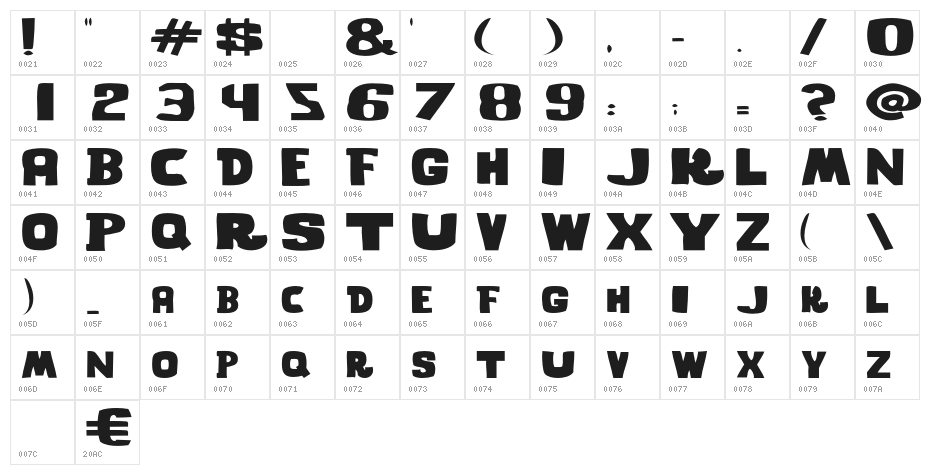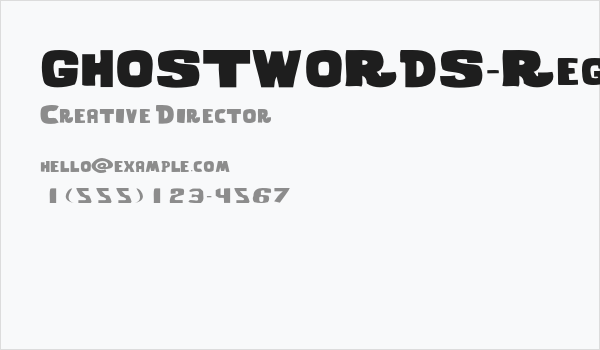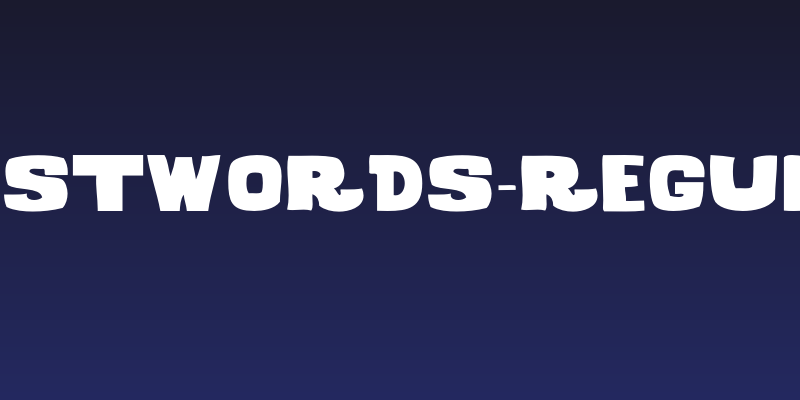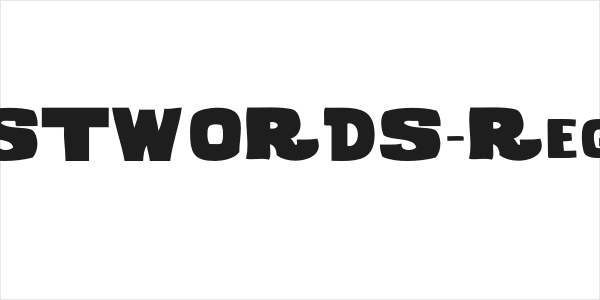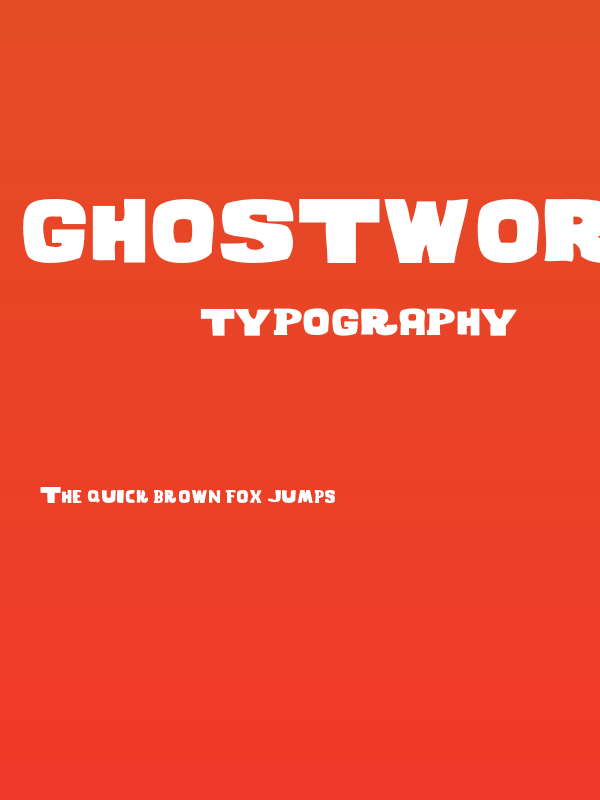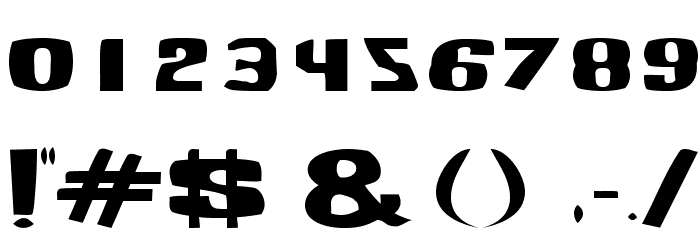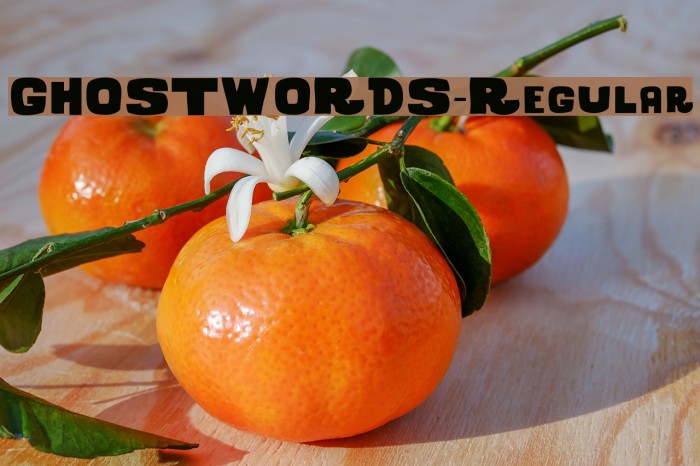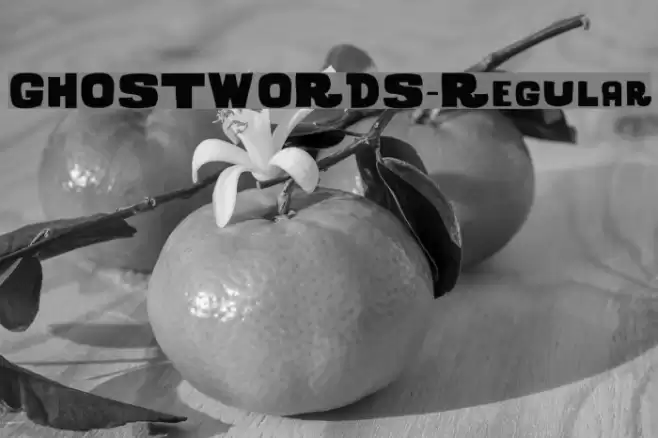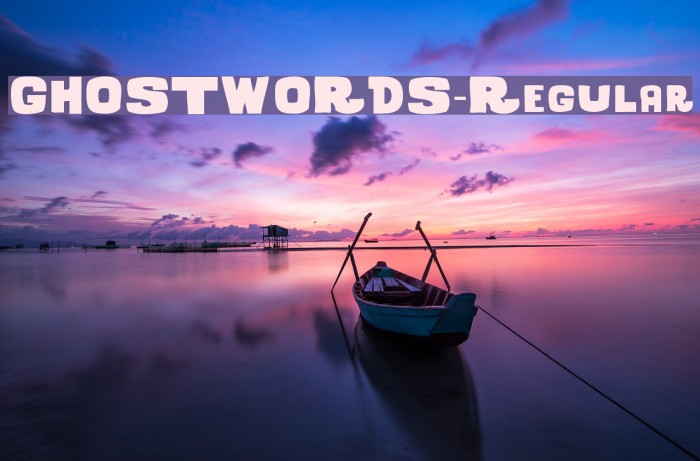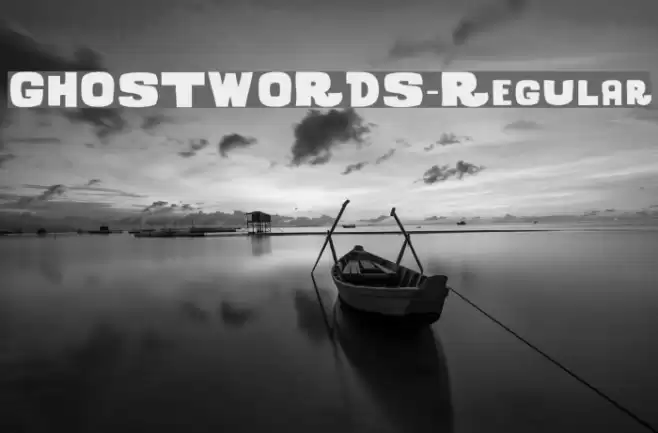
GHOSTWORDS-Regular Font
✎ Comic
| Categorías | Comic |
| Estilo general | Vintage, Decorative |
| Caso de uso | Headlines, Posters, Themed Events |
| Proyectos propuestos | Ideal for Halloween-themed designs, posters, party invitations, or any project requiring a fun and spooky aesthetic. |